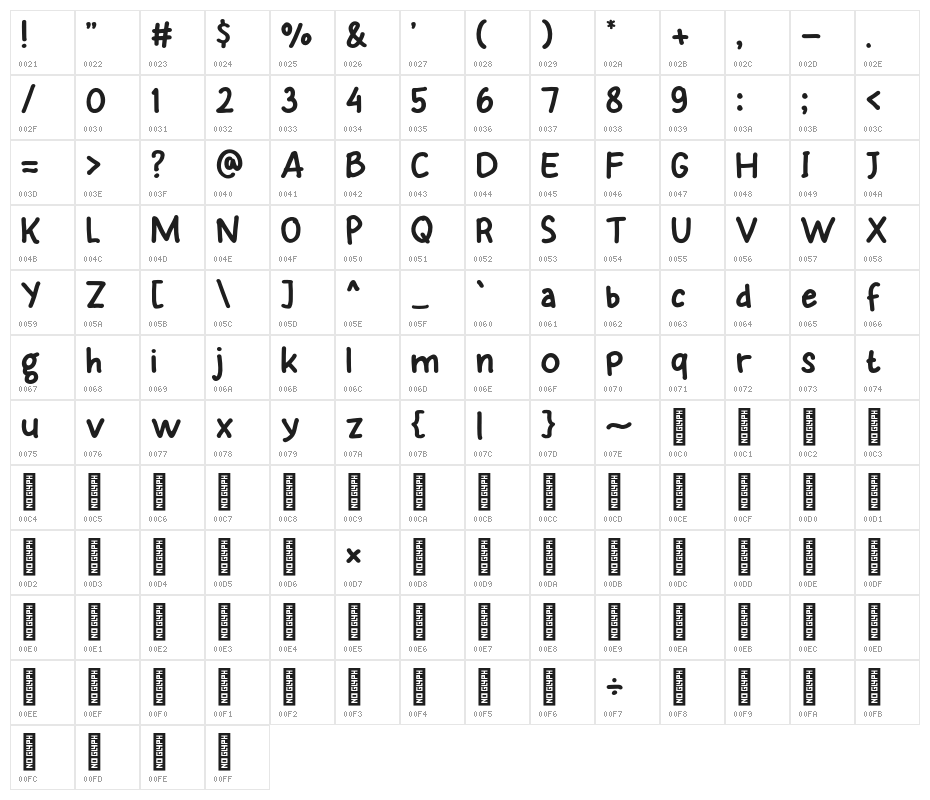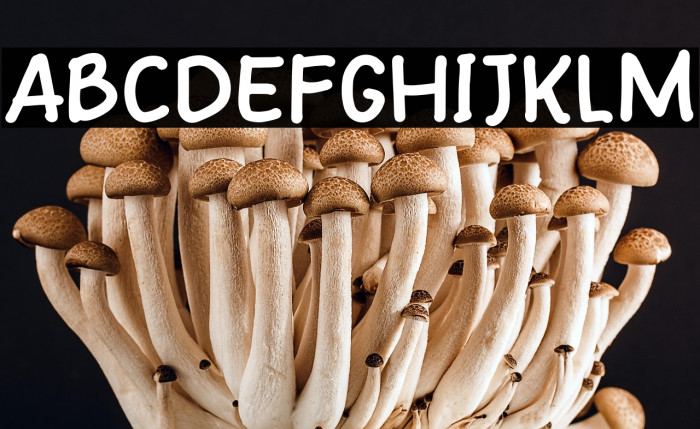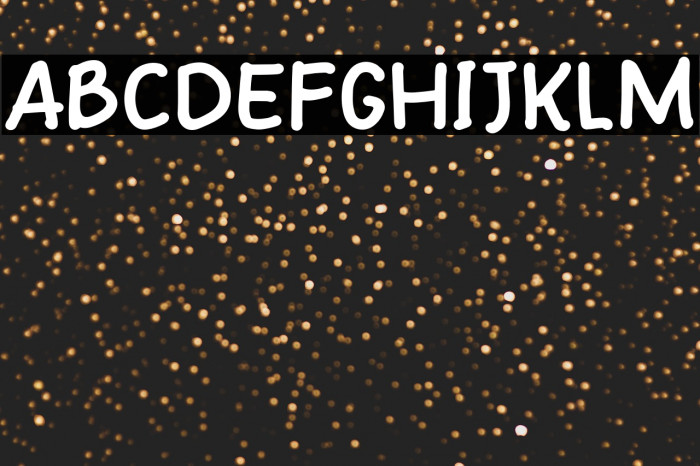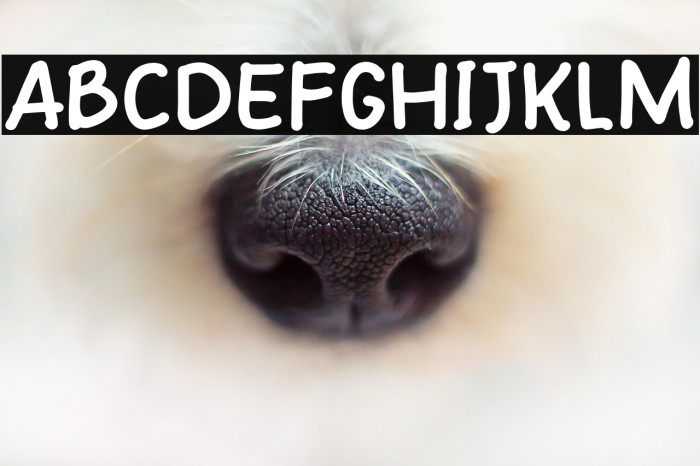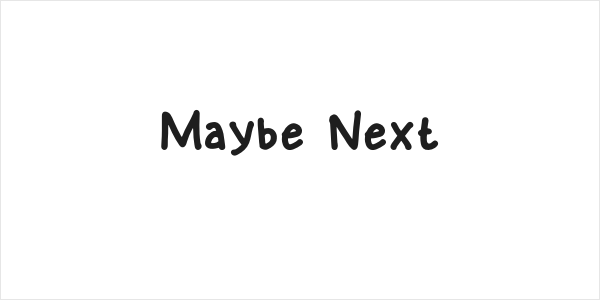
Maybe Next Font
| Gesamtstil | Casual, Playful |
| Anwendungsfall | Headlines, Informal text, Creative projects |
| Vorgeschlagene Projekte | Ideal for children's books, casual invitations, playful branding, and creative posters. |